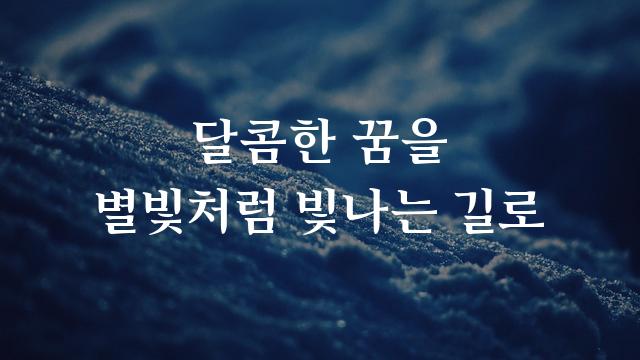
아리따돋움은 아모레퍼시픽에서 제작한 기본 고딕 스타일의 한국어 폰트로, 꽉 찬 느낌의 고딕이 특징입니다. 현대적이면서도 읽기 쉬운 디자인으로 다양한 매체에 활용하기 좋습니다.
아리따돋움은(는)
기본 고딕, 굵은 고딕, 감성적인, 단단함, 부드러움 계열의 생김새를 가지고 있으며
웹/앱 디자인, 보고서/문서, 출판물 제목 등에서 자주 활용되며, 효과적인 메시지 전달에 적합합니다.
이 폰트는 출판/미디어, 기술/IT, 금융/비즈니스 분야에 잘 어울리며,
세련된, 명확한, 전문적인 느낌을 담고 있는 것이 특징입니다.